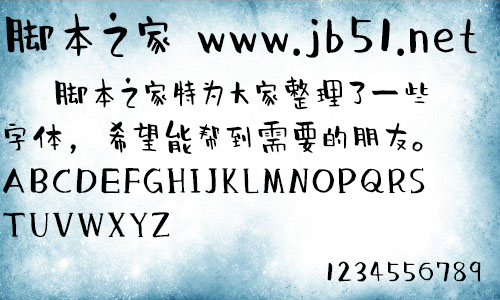
百家造字胖小六體
百家造字胖小六體一款不錯(cuò)的藝術(shù)字體,由百家字庫(kù)出品,字體筆觸粗細(xì)交織,字形圓潤(rùn)可愛,具有很好的視覺感,適合應(yīng)用于藝術(shù)設(shè)計(jì)、平面宣傳設(shè)計(jì)、網(wǎng)頁(yè)設(shè)計(jì),書法字帖等領(lǐng)域,需要的朋友可以前來本站下載。